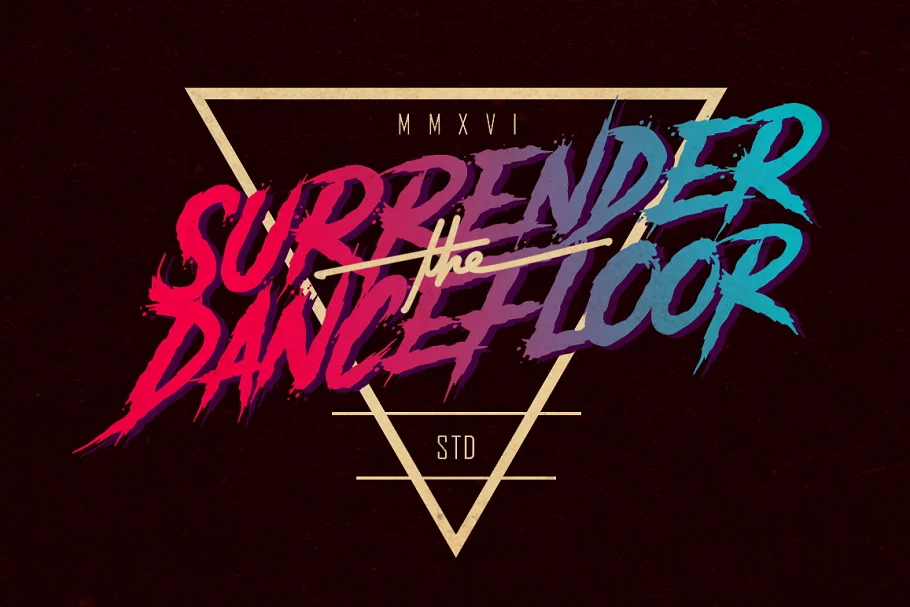
Little Samurai Font
Description de Little Samurai Font
Le Little Samurai est une police d’affichage audacieuse et amusante, au style frais et moderne. Little Samurai Font adaptée au logo, à la marque, à la carte de vœux, à l’affiche et à tout design que vous créez.
Khurasan